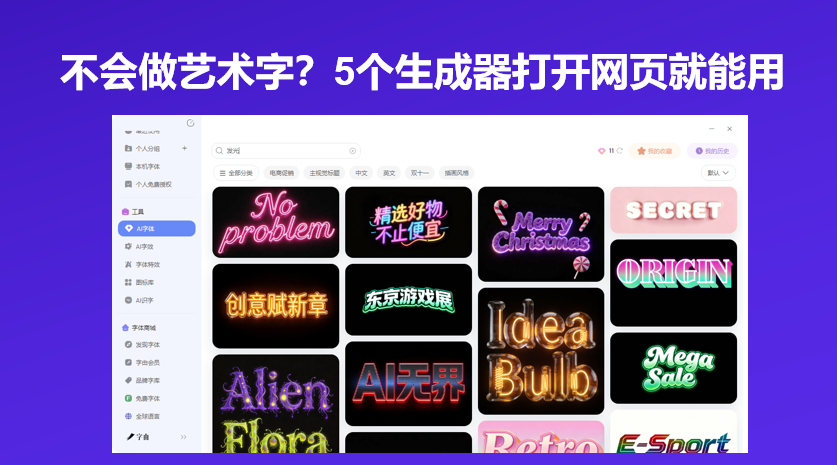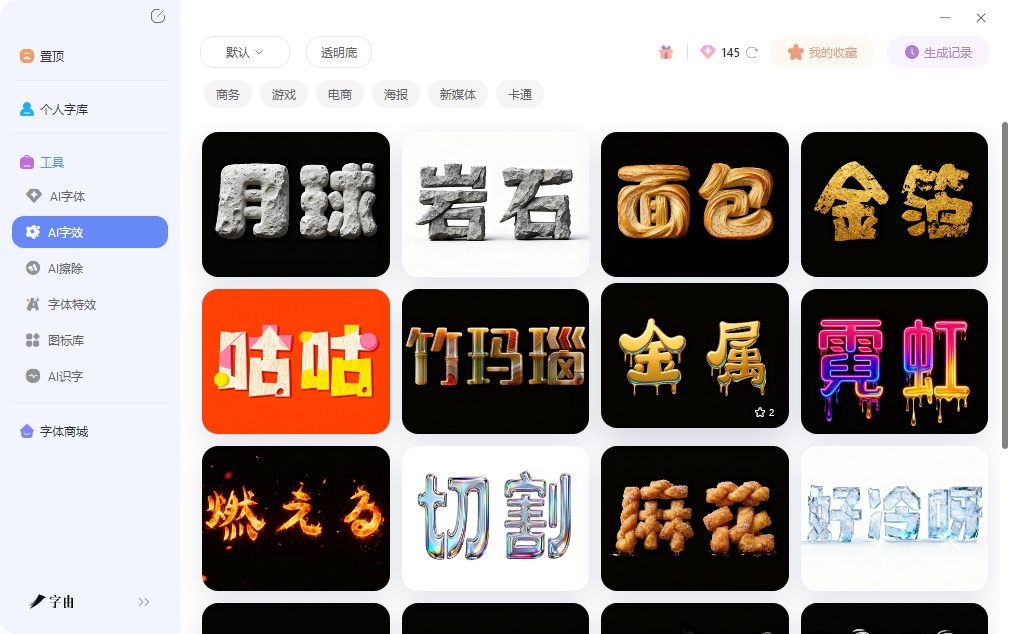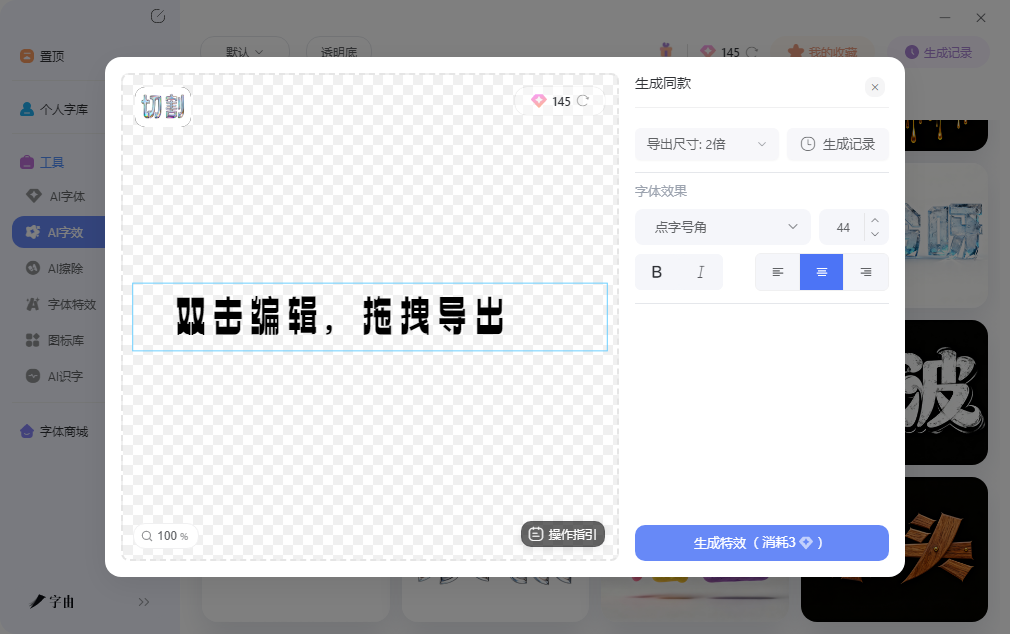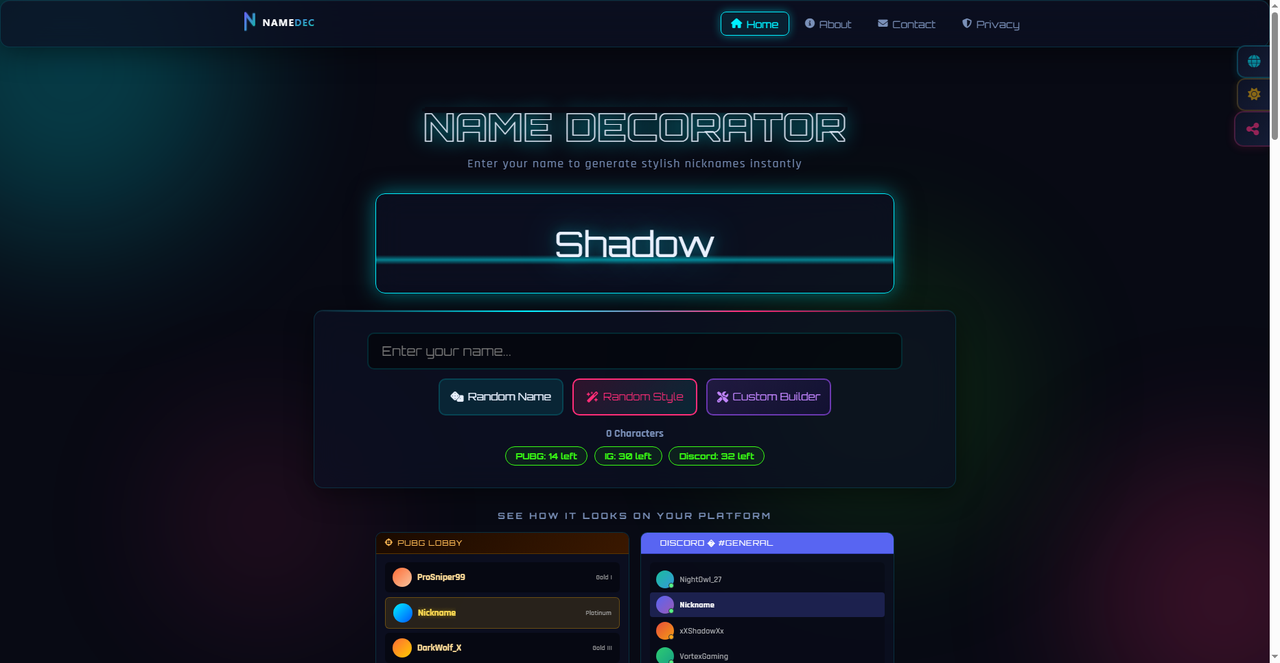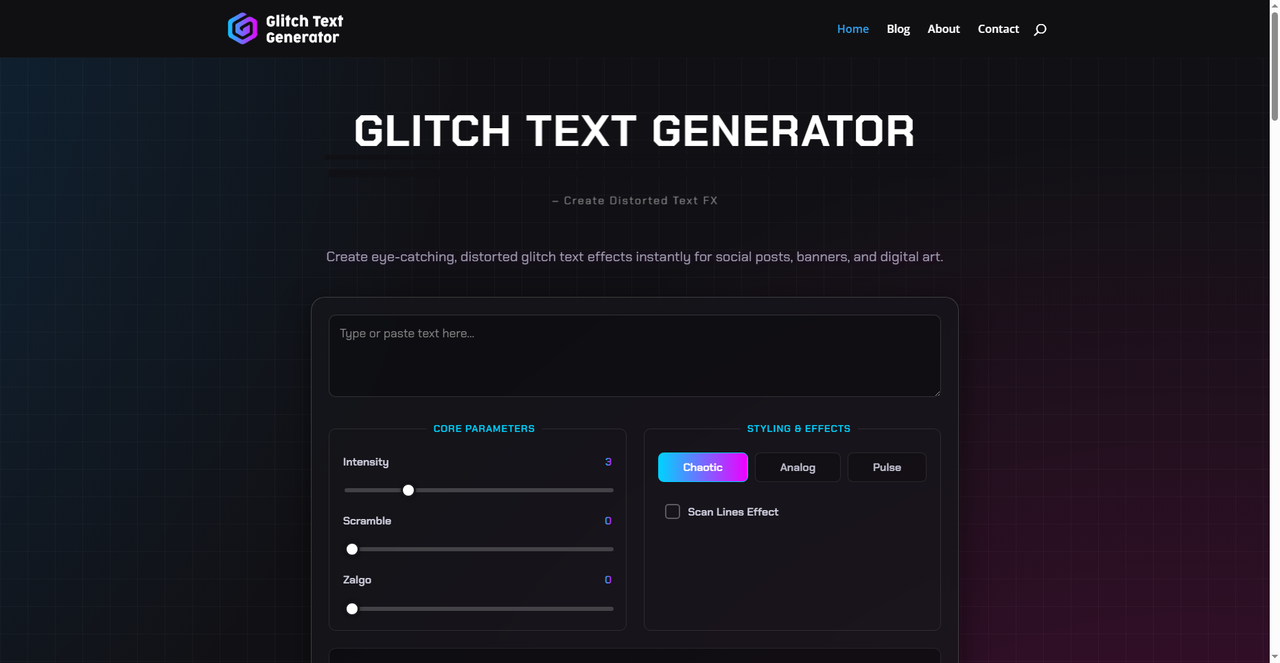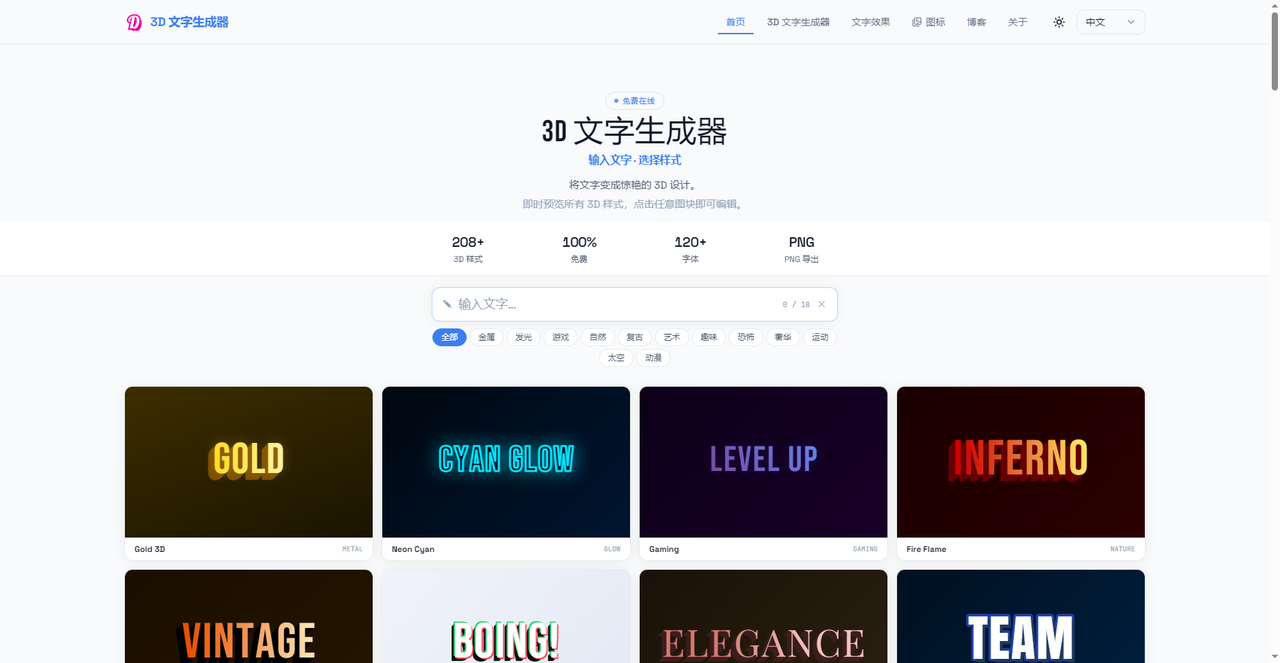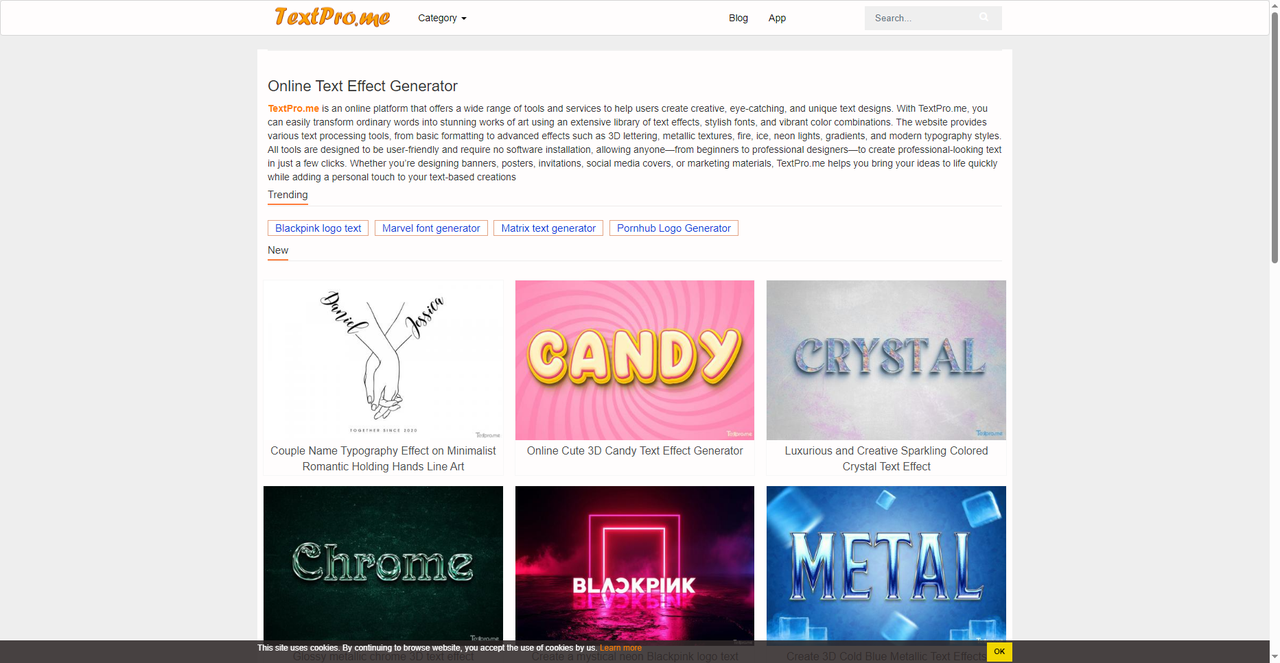
不会做艺术字?5个生成器打开网页就能用
做海报标题或者社交媒体封面时,文字往往是视觉重心。但很多人不会用PS的图层样式,调出来的效果总是不如预期。去网上搜教程学做金属字、霓虹字,看完视频自己操作还是一团糟,最后放弃用回默认字体。其实现在不少网页工具专门解决这个痛点,打开浏览器输入文字就能生成带特效的艺术字图片,几分钟出一张带透明背景的PNG,直接拖进设计软件继续排版。这篇文章整理的几个生成器,有的专攻立体效果,有的擅长故障风格,有的支持3D渲染,都可以尝试一下。
字由里有个AI字效功能,在出艺术字图片这个方向上比较直接。输入文案后选择特效类型,霓虹、金属、浮雕、投影等方向都有覆盖,每种效果下还有细分变体,比如金属类就分拉丝、镜面、生锈等不同质感。调好色温、强度、光影角度后,生成的是带透明背景的PNG图片,可以直接拖进PS、AI、Sketch甚至PPT里,不需要额外抠图。
这个功能对临时需要做几张图但电脑里没有装设计软件的人很友好,打开浏览器就能出图。登录后有一定免费额度,预览阶段不消耗,确认效果后再正式输出,对偶尔做几张图的用户比较友好。特效类型包括霓虹发光、金属拉丝、立体浮雕、投影阴影等常见效果,每种效果下还有细分变体可选。
除了出特效图,字由里收录的字体本身也能配合这个流程。做艺术字前先确定字体风格,再在字体库里浏览手写体、书法体、展示体等方向,找到气质匹配的字体激活试用,确认效果后再加AI字效,整个流程比较顺畅。字体库里有明确标注免费商用的字体,商用前确认授权状态即可。
和纯网页生成器相比,字由的优势在于字体和特效可以组合。网页工具通常只提供固定模板,字体不可更换;字由可以先选字体再加特效,做出来的艺术字风格更独特。对于需要做系列物料或者追求风格统一的项目来说,这种组合方式比单用网页模板更灵活。
2、Name Decorator
Name Decorator是一个偏向装饰性文字生成的在线工具,核心功能是把名字或者短文案转换成带有装饰元素的艺术字图片。输入文字后,系统会生成多种装饰方案,包括花卉缠绕、几何边框、星星点缀、爱心环绕等效果。每种装饰方案都有独特的视觉层次感,花卉缠绕适合浪漫主题,几何边框适合现代风格,星星点缀适合节日氛围,爱心环绕适合温馨场景。网站支持调整装饰密度、主色和背景色,调好后实时预览,确认无误再下载。生成结果可以下载PNG图片,透明背景,直接放进贺卡、邀请函或者社交媒体配图里。
3、Glitch Text Generator
Glitch Text Generator是一个专注故障艺术风格的在线工具,核心功能是把普通文字转换成带有数字故障效果的图片。输入文字后,系统会生成多种故障风格,包括RGB分离、像素错位、扫描线干扰、信号丢失等效果。每种故障类型都有独特的视觉破坏感,RGB分离适合科技感主题,像素错位适合复古游戏风格,扫描线干扰适合赛博朋克氛围,信号丢失适合末日废土风格。网站支持调整故障强度、颜色偏移量和错位频率,调好后实时预览,确认无误再下载。
4、3D Text Generator
3D Text Generator是一个专门做立体文字效果的在线工具。进入网站后输入文字内容,选择3D风格模板,系统会实时渲染出带深度和透视的立体文字。可以调整文字的厚度、倒角角度、表面材质和光源方向,做出从轻微浮雕到强烈挤压的各种立体效果。生成结果支持下载PNG图片,带透明背景,直接放进海报或者PPT里就能用,不需要额外抠图。
网站的操作界面比较直观,左侧是文字输入区,右侧是参数调节面板。材质选项包括金属、塑料、玻璃、木纹等常见类型,每种材质下又有细分变体。光源可以手动拖拽调整方向,想看正面打光还是侧面打光,拖动滑块实时就能看到变化,这种所见即所得的调节方式比输入数值更直观。
5、TextPro
TextPro是一个老牌在线文字特效平台,模板库覆盖了金属、火焰、冰晶、木纹、大理石、霓虹等几十种材质效果。选择模板后输入文字,可以调整主色、辅色、光影角度、表面纹理、文字间距等参数,生成高分辨率的PNG或GIF。网站支持中文输入,部分模板对中文字符的渲染效果不错,笔画细节处理比较到位,做中文海报时不会出现笔画粘连。
TextPro的模板库覆盖面广,各种材质都能找到;3D Text Generator的立体效果适合需要深度感的标题;Glitch Text Generator的故障风格适合科技和电竞主题;Name Decorator的装饰效果适合个性化贺卡。字由在字体和特效组合方面比较灵活,从选字体到出艺术字图都能在客户端内完成。按自己的使用场景来选,偶尔做几张图用网页工具足够,长期做设计可以搭配字由一起用,字体和特效的组合会更灵活。